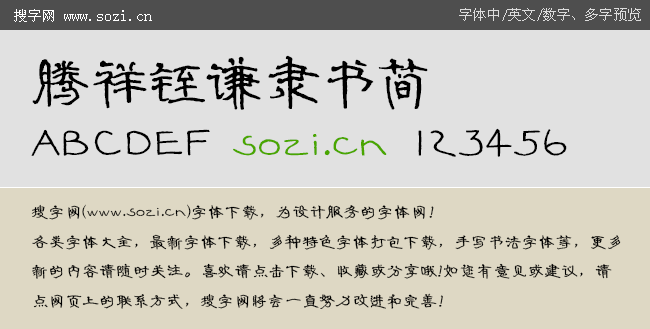
騰祥铚謙隸書簡(jiǎn)
搜字網(wǎng)提供一款騰祥铚謙隸書簡(jiǎn)中文藝術(shù)字體下載,騰祥铚謙隸書繁字體是一款手寫風(fēng)格的隸書字體,字體樸素?zé)o華,飽含古時(shí)之風(fēng)韻。 可用于出版印刷、廣告設(shè)計(jì) 網(wǎng)頁(yè)設(shè)計(jì)、包裝設(shè)計(jì)、屏幕顯示等領(lǐng)域。